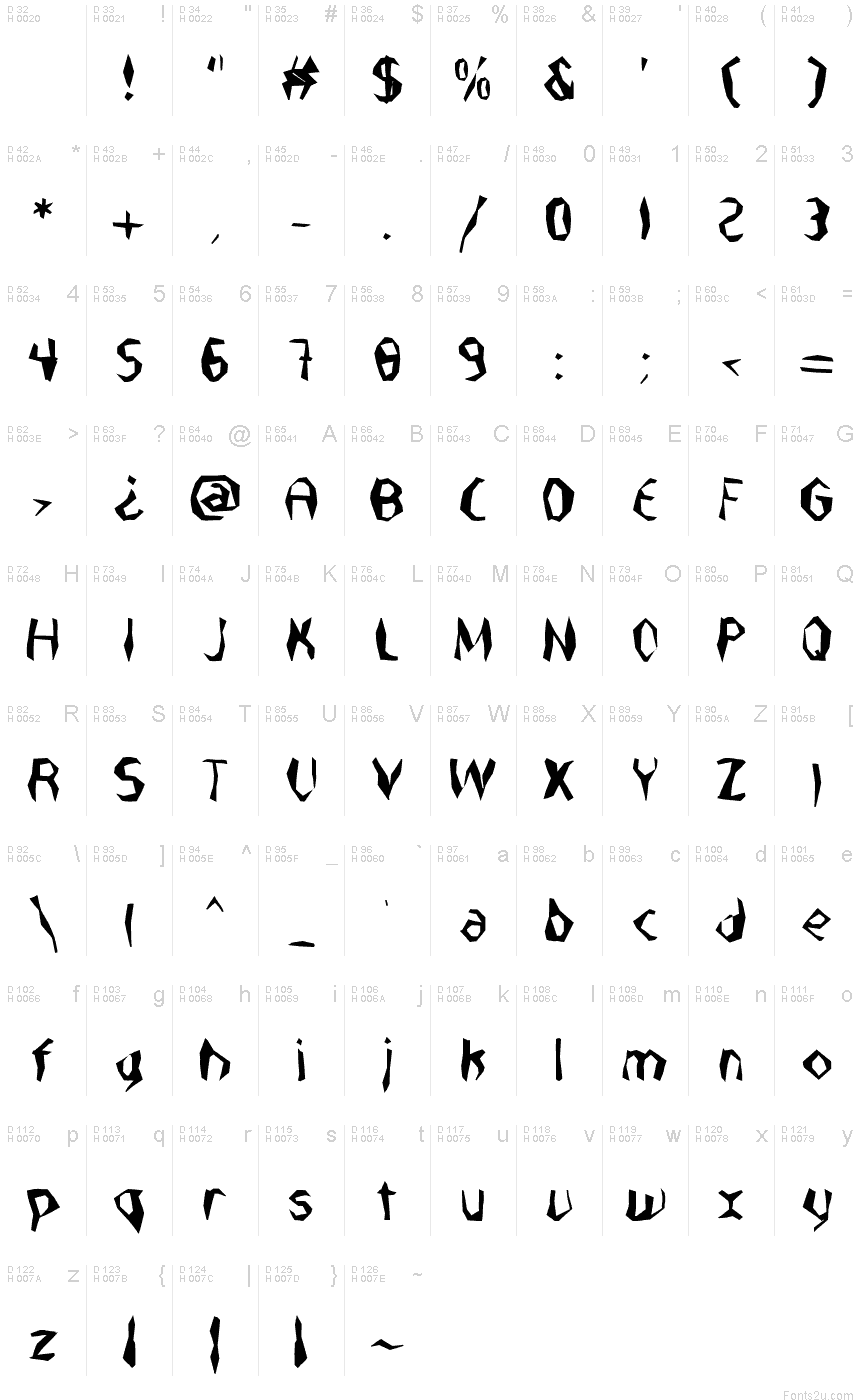
Nabatea
Nabatea es una letra hecha a colpe de mazo, sobre la dura piedra, por el individuo de un antiguo pueblo de la Arabia Ptrea, entre el mar Rojo y el ro ufrates. La tipografa es un homenaje a Petra, capital nabatea.
Esta es una fuente con personalidad para usarla en Carteles y posters tipogrficos, logos o ttulos. Saludos.